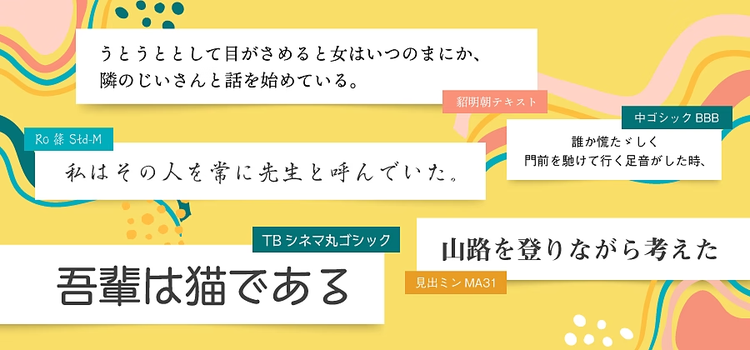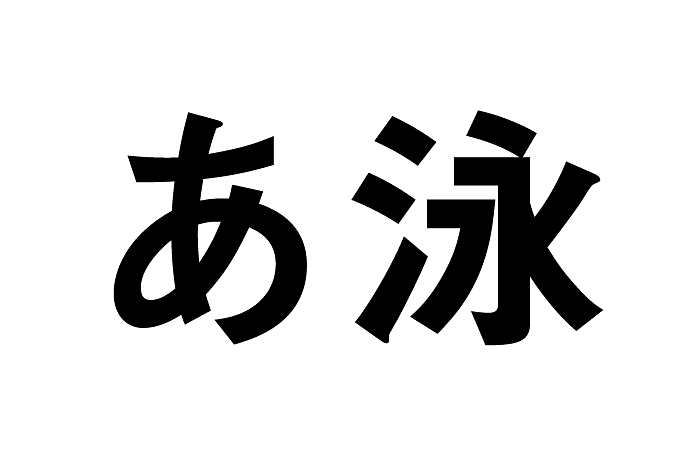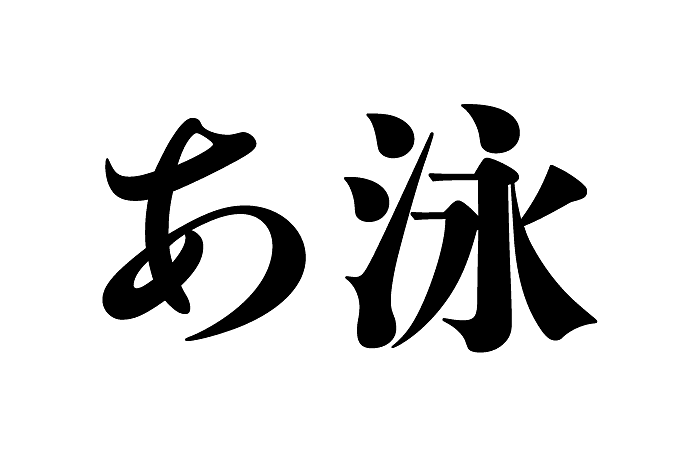
ウェブフォントの選び方と使い方
デザインの大切な要素のひとつがフォントです。
特に文字要素の多いWebサイトを作るときには、フォントがサイト全体の印象を決めると言っても過言ではありません。
Webに最適なフォントの選び方とWebフォントの上手な使い方を紹介します。
Webに最適なフォントの選び方
デザイナーには適切なフォントを選ぶ力が求められます。Webに最適なフォントの選び方を紹介します。
標準フォントを表示させるべきか
まず、標準フォントとは、もともとコンピュータに入っているフォントのことです。デバイスフォント、システムフォントとも呼ばれます。
商品やサービスのイメージや世界観に合ったフォントを探したり、選んだりするのは楽しくもありますが、Webサイトのデザインをする場合には「ユーザーの閲覧環境の違い」を意識してフォントや実装方法を決める必要があります。
「閲覧環境」とは、たとえばOSの違いです。
同じWebサイトを見ていても、サイト側でフォントが何も指定されていない場合(※1)ユーザーが最初から持っている標準フォントが表示されます。
たとえばWindowsでは「メイリオ」、macOSやiOSでは「ヒラギノ角ゴシック」、Androidであれば、6.0以降で「Noto Sans CJK JP」が表示される仕組みとなっています。
つまり意図して実装しない限りは、同じサイトであっても同一の文字は表示されないのです。
Noto Sans CJK JPのフォント例
各社が標準で搭載しているこれらの「標準フォント(デバイスフォント、システムフォント)」は、いずれもスクリーンでの可読性が高いフォントですが、同じゴシック体でも印象が異なることがわかります。
そこで、実際のWebサイト制作では別のフォントを指定するケースも多くあります。
(※1 フォントの種類を指定するCSS(font-familyプロパティ)が設定されていない状態)
明朝体よりゴシック体?スクリーンに適したフォントを選ぶ
それでは、スクリーンで見る文字に適したフォントとはどのようなものでしょうか。
まずは明朝体とゴシック体について考えてみましょう。
特に指定がない場合に表示されるフォントは、いずれもゴシック体です。システムフォントの中には明朝体もありますが、なぜゴシック体が優先されて表示されるのでしょうか。
明朝体は、細い横画やウロコ、はらいといったの緩急豊かな形が特徴です。
印刷物で利用すると読みやすくて情趣ある美しいフォントも多い一方で、細くて小さいサイズの明朝体を解像度の低いスクリーンで見ると、細い部分がかすれたように表示され、読みづらく感じられることがあります。
緩急が豊かな明朝体のフォント例
緩急が豊かな明朝体
線がほぼ均一なゴシック体のフォント例
線がほぼ均一なゴシック体
明朝体:DNP 秀英初号明朝 Std ゴシック体:
それに対してゴシック体は、線がほぼ均一なので読みやすさが解像度に左右されにくいという特徴があります。そのためアンチエイリアス(※2)処理の無い低解像度のディスプレイが多数を占めていた時代から、多くのWebサイトで用いられていたため、今日でもたくさんのWebサイトがゴシック体を採用しています。
近年はスクリーンの高解像度化とブラウザやCSSの進歩により、フォントの精細な表現も実現可能になりました。しかしながら、ユーザーによってスクリーンの解像度がまちまちなことを考えると、Webサイトにおける長いパラグラフ(本文)については、まずはゴシック体を検討するのがおすすめです。
(※2 斜めの線などをなめらかに見せる処理)
スクリーン幅の違い(改行位置)を考える
解像度の違いのほかにも、スクリーン幅の違いにも気を配る必要があります。
PC、タブレット、スマートフォンといった異なる画面幅に応じてレイアウトを変える「レスポンシブWebデザイン」は幅に応じて改行位置が変化するので、印刷物のように厳密な字切り(改行)の管理が難しいのです。
明朝体:DNP 秀英初号明朝 Std ゴシック体:
それに対してゴシック体は、線がほぼ均一なので読みやすさが解像度に左右されにくいという特徴があります。そのためアンチエイリアス(※2)処理の無い低解像度のディスプレイが多数を占めていた時代から、多くのWebサイトで用いられていたため、今日でもたくさんのWebサイトがゴシック体を採用しています。
近年はスクリーンの高解像度化とブラウザやCSSの進歩により、フォントの精細な表現も実現可能になりました。しかしながら、ユーザーによってスクリーンの解像度がまちまちなことを考えると、Webサイトにおける長いパラグラフ(本文)については、まずはゴシック体を検討するのがおすすめです。
(※2 斜めの線などをなめらかに見せる処理)
スクリーン幅の違い(改行位置)を考える
解像度の違いのほかにも、スクリーン幅の違いにも気を配る必要があります。
PC、タブレット、スマートフォンといった異なる画面幅に応じてレイアウトを変える「レスポンシブWebデザイン」は幅に応じて改行位置が変化するので、印刷物のように厳密な字切り(改行)の管理が難しいのです。
デバイスの種類(幅)によって文字の改行も変化することを前提にサイトを設計することがわかる画面例
デバイスの種類(幅)によって文字の改行も変化することを前提にサイトを設計する
こうしたスクリーンの解像度や幅の違いも「ユーザーの閲覧環境の違い」のひとつとして考えるべきでしょう。最終成果物(紙)のサイズがひとつしか存在しない印刷物のデザインと違って、Webデザインではサイズは千差万別です。
こうした違いをふまえてフォントの種類と実装方法を選んでいく必要があります。
システムフォント以外のフォントをWebで使う方法
システムフォント以外のフォントをWebで使うための、主な2つの方法を紹介します。
1.フォントを画像にして使う(非推奨)
デバイスフォント以外のプロが使う高品質のフォントをWebサイトで使うためには、かつてはAdobe IllustratorやAdobe Photoshop内で作ったテキストを画像として貼り付けるという方法が主流でした。ただし、デメリットが多いやり方となっています。
スクリーンサイズや解像度対応が難しい
ところがこの方法は改行や文字詰めがデザイナーの思い通りになる反面、無数にあるスクリーンサイズやその解像度すべてに対応するのは難しいという問題点があります。
たとえば、従来のディスプレイ解像度に合わせた文字画像(72ppi)を、いまのMacやスマートフォンの高画素密度のディスプレイで見ると、ボヤケて読みづらくなります。
文字が読みづらい、修正ができない
ほかにも画像化した文字がスクリーン幅によっては小さくて読みづらい、文字のコピー&ペーストができない、特定のフォントが入ったマシンでないと文字の修正ができないといった不便さやトラブルもあります。
画像からフォントを作成すると文字が小さくなって読みにくくなったことがわかる画面例
Webアクセシビリティに配慮できない
また、Webサイトを実装する上では、特に障がいや高齢という理由で視覚に制約があるユーザーに対する「Webアクセシビリティ(a11y)」に配慮する必要性もあります。
WebアクセシビリティはJISで国内標準が策定されていて多種多様な対応ポイントがありますが、HTMLファイルを読み上げソフト(スクリーンリーダー、音声ブラウザ)で読み上げた際に音として意味がきちんと伝わるかどうかがポイントのひとつです。
これを考慮せずに「制作者のPCで見たときの美しさ」だけを優先して文字を画像として扱うと、結果として多くの人に情報を伝える機会を失うことにもなりかねません。
SEO効果が得られにくい
また、文字は文字として情報を持たせておいたほうが検索にひっかかりやすいため、検索結果を上位に表示させるための「SEO」(※3)の観点からも、文字情報は極力画像化せずに、HTMLの中できちんと記述されるのが望ましいと言えます。
画像からフォントを作成するとSEO効果が得られにくいことをイメージした画
しかしながら、システムフォントだけでは表現の幅が狭くなってしまうことは否定できません。WebアクセシビリティやSEOに配慮しつつ、印刷物のデザインのように美しいフォントを使ってWeb上で文字を組むのは多くのWebデザイナーが長年望んでいた技術でした。
(※3 SEO:Search Engine Optimization,検索エンジン最適化)
2. Webフォントを表示させる
そこで登場した技術が「Webフォント」です。
Webフォントとは、Webサーバーからフォントのデータを配信して表示する仕組みのことを指します。このWebフォントの登場により、ユーザーが持つシステムフォント以外の選択肢が生まれ、高品質の美しいフォントを柔軟に利用できるようになりました。
サーバーを介してフォントの情報を取得するので、文字の種類が多い日本語では読み込みが若干遅くなるというデメリットもありましたが、近年はダイナミックサブセット(※4)といったの技術によって、こうした表示の遅延問題も解消されつつあります。
(※4 必要な文字の形だけをサーバー側にリクエストする技術。Adobe FontsのWebフォントでもこれを採用している)
きれいにフォントを表示させるCSSの指定方法
システムフォントやWebフォントを問わず、Webで文字を扱うためにはCSSプロパティの理解が不可欠です。ここでは文字の設定や文字組みに関するCSSプロパティについて紹介します。
きれいにフォントを表示させるCSSの指定例
font-family
font-familyとは、フォントの種類を指定するプロパティです。
font-familyとは、プロパティの中にWebフォントの指定をすることで、Webフォントが表示されます。
font-familyプロパティは複数のフォントを指定でき、先に書いたものが優先されるという性質があります。先に欧文フォントを指定し、2番目に和文フォントを指定することで、英数字だけを特定のフォントに置き換える和欧混植も可能です。
color
colorとは、フォントの色を指定するプロパティです。
#からはじまるHex値のほか、RGBやアルファ(透過)を含めたRGBaでも指定が可能です。色の選定にあたっては、背景色と文字色のコントラスト比も可読性の重要な要素となってきます。
font-weight